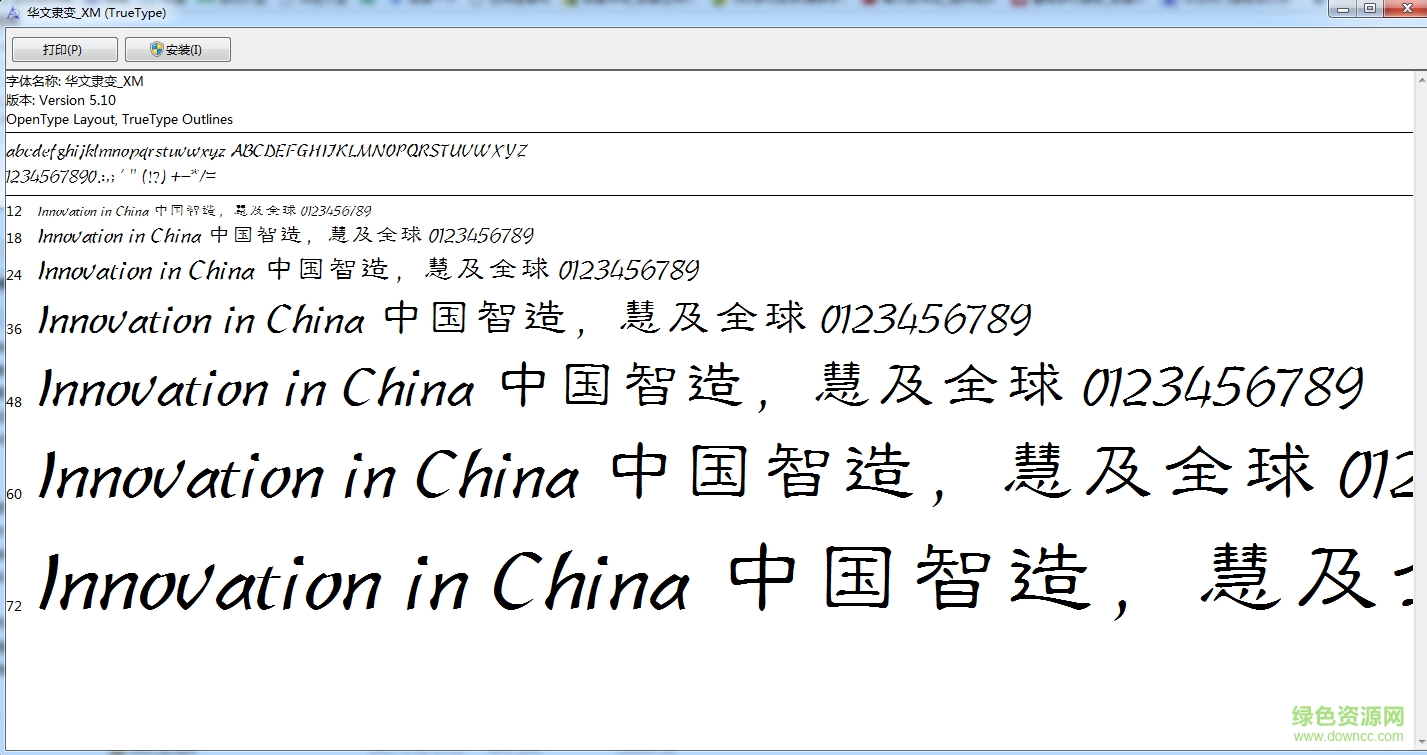
stlibian sc regular是什么字體?stlibian sc regular字體就是華文隸變字體,該字體字形優(yōu)雅,結(jié)構(gòu)穩(wěn)定,整體端正大氣,富于生命力,歡迎大家免費(fèi)下載!
字形扁方左右分展
起筆蠶頭收筆燕尾
化圓為方化弧為直
變畫為點(diǎn)變連為斷
強(qiáng)化提按粗細(xì)變化